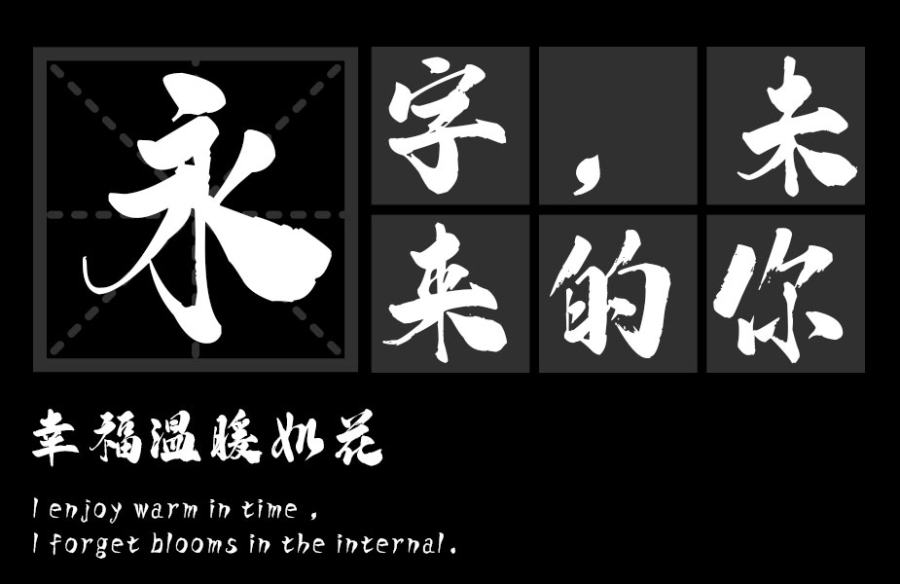
汉标高清锐毛字体发布
字体名称:汉标高清锐毛
字体类别: 毛笔书法
汉标高清锐毛字体简介:书法味道的纯手写字体,作者运用大号毛笔精心书写,楷书味道浓厚,由于字体较大,使得笔画清晰度较高,笔画中也减少了过多的处理和笔势,厚重、饱满。因为是纯手写的原因,它独特的气质更与其他字体不同,看似统一,其实各有各的味道,每个字都可以独具风情。
汉标高清锐毛预览图展示: